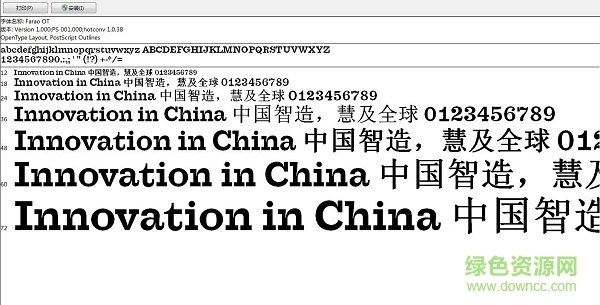
faraoot-bold
farao ot字體是一款細(xì)節(jié)方法的高品質(zhì)襯線字體,線條舒展,氣質(zhì)好,給人的感覺(jué)十分優(yōu)雅,適合用在雜志、古典書籍、平面設(shè)計(jì)等領(lǐng)域,需要的朋友千萬(wàn)不要錯(cuò)過(guò),快來(lái)免費(fèi)下載吧!